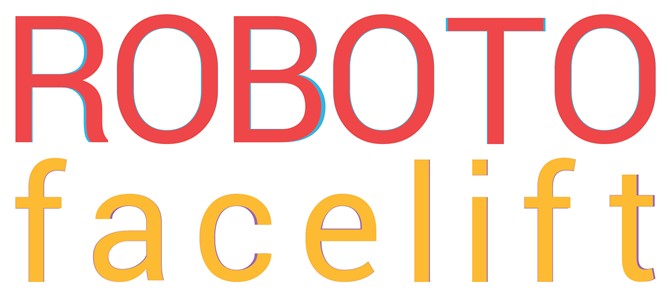
Android 4.3: leggeri cambiamenti anche sul font
Da qualche giorno è apparso, grazie al Galaxy s IV Google Edition, l’aggiornamento Android 4.3 grazie al quale stiamo apprendendo molte indiscrezioni sul nuovo update del sistema operativo del robottino verde
Secondo quanto appreso ogni angolo del software è stato modificato e migliorato o comunque revisionato, i tecnici di Google non stanno mai con le mani in mano in pratica non tralasciando nemmeno i piccoli dettagli. Una delle parti prese in esami e migliorate sembra infatti essere il font che rimane sempre Roboto ma con qualche lieve modifica.
Come potete notare dall’immagine sopra, linee rosse nuova versione linee nere vecchia versione, il font rimane sempre nello stesso stile ma leggermente affinato e ripulito.
In particolare le modifiche riguardano le curve delle lettere, sopratutto sulle minuscole che sono state rifilate. Altri miglioramenti sono stati fatti invece sulla punteggiatura in particolare sulla virgola.